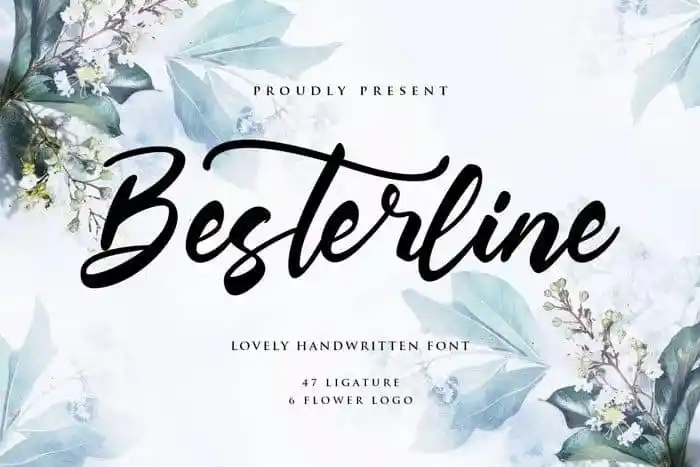
Besterline Script Font – Download Grátis
A Besterline Script Font é uma fonte em estilo script criada com uma autêntica aparência de escrita manuscrita. Desenhada e compartilhada pelo designer Rantautype, esta fonte possui um visual natural que adicionará um toque natural a seus próximos projetos. Inspirado na sua singularidade única, a Besterline Script Font é perfeita para criar designs, logos, embalagens de produtos ou cartazes e muito mais. Esta fonte traz uma nova dimensão ao seu trabalho gráfico, tornando-o ainda mais autêntico e personalizado. Se você está procurando por uma fonte que seja tanto estilizada quanto natural, a Besterline Script Font provavelmente será o elemento perfeito para completar seus projetos em 99designs.